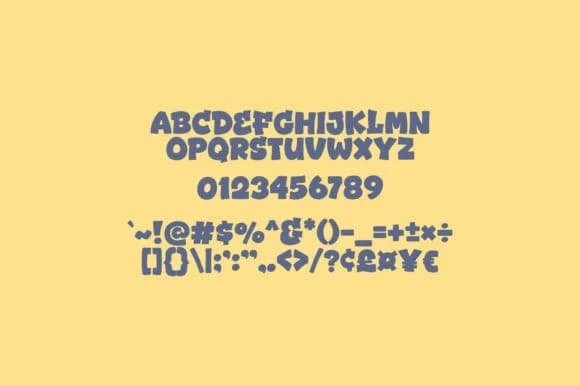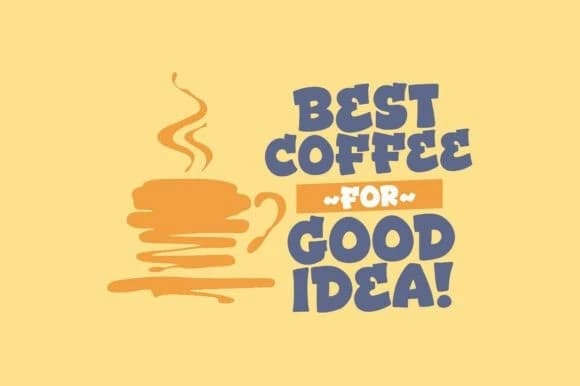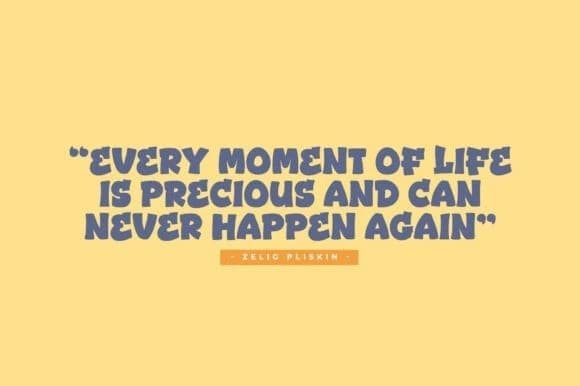
Street Year Yazı Tipi
Street Year Font, posterler, logolar, dergiler, kitap kapakları, afişler ve çok daha fazlası için mükemmel, modern ve sevimli bir display fontudur! Bu harika fontu edinin ve onu güzel tasarımlar yaratmak için kullanın. Oldukça geniş bir proje yelpazesine kolayca uyum sağlar.
Street Year Font, posterler, logolar, dergiler, kitap kapakları, afişler ve çok daha fazlası için mükemmel, modern ve sevimli bir gösterim yazı tipidir! Bu harika fontu edinin ve onu güzel tasarımlar yaratmak için kullanın. Çok geniş bir proje yelpazesine kolaylıkla uyum sağlar.